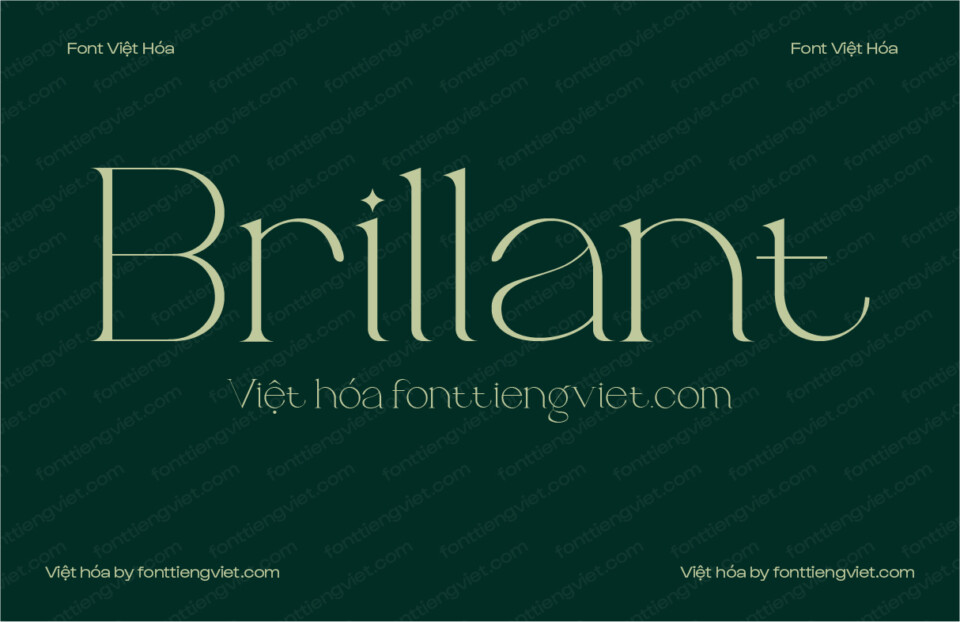
Font Việt hóa 1FTV VIP Brillant
Giới thiệu về bộ Font Việt hóa 1FTV VIP Brillant
Trong thế giới thiết kế đồ họa hiện đại, việc lựa chọn một phông chữ phù hợp đóng vai trò quyết định đến linh hồn của tác phẩm. Font Việt hóa 1FTV VIP Brillant nổi lên như một hiện tượng trong cộng đồng designer Việt Nam nhờ sự kết hợp hoàn hảo giữa nét cổ điển và hơi thở đương đại. Đây là bộ Font Miễn Phí được tinh chỉnh kỹ lưỡng để hỗ trợ đầy đủ các ký tự tiếng Việt, giúp người dùng không còn lo lắng về lỗi hiển thị dấu hay khoảng cách chữ không đều. Với cấu trúc đường nét thanh mảnh nhưng vô cùng chắc chắn, bộ chữ này mang lại cảm giác chuyên nghiệp và đẳng cấp cho mọi khung hình. Đặc biệt, phiên bản 1FTV VIP Brillant này đã được tối ưu hóa để hiển thị sắc nét trên cả màn hình kỹ thuật số lẫn các ấn phẩm in ấn vật lý, đáp ứng nhu cầu khắt khe của các chuyên gia sáng tạo.
Đặc điểm nổi bật của Font Việt hóa 1FTV VIP Brillant
Thiết kế sang trọng và tinh tế
Điều đầu tiên khiến Font Việt hóa 1FTV VIP Brillant thu hút sự chú ý chính là sự chỉn chu trong từng nét chữ. Các đường cong được vuốt nhẹ nhàng, tạo nên sự uyển chuyển nhưng không kém phần mạnh mẽ. Đây là lựa chọn lý tưởng cho các dự án thiết kế thương hiệu cao cấp, thiệp mời sự kiện hoặc các bìa tạp chí thời trang. Sự cân bằng giữa các ký tự giúp văn bản trở nên dễ đọc, tạo cảm giác dễ chịu cho người xem ngay từ cái nhìn đầu tiên.
Khả năng tương thích đa dạng
Ứng dụng thực tế của Font Việt hóa 1FTV VIP Brillant
Trong thiết kế truyền thông và quảng cáo
Với phong cách VIP đầy ấn tượng, phông chữ này thường xuyên xuất hiện trong các chiến dịch quảng cáo sản phẩm làm đẹp, trang sức và bất động sản. Việc sử dụng Font Việt hóa 1FTV VIP Brillant giúp tiêu đề của bạn trở nên nổi bật, thu hút sự chú ý của khách hàng mục tiêu và nâng tầm giá trị cho thông điệp truyền tải. Những đường nét tinh xảo của bộ chữ góp phần xây dựng lòng tin và sự chuyên nghiệp cho hình ảnh thương hiệu trong mắt công chúng.
Trong giáo dục và đời sống hàng ngày
Tại các nhà trường, các thầy cô giáo có thể ứng dụng bộ chữ này để thiết kế bằng khen, chứng chỉ hoặc các tài liệu giảng dạy sinh động. Sự rõ ràng của Font Việt hóa 1FTV VIP Brillant giúp học sinh dễ dàng tiếp nhận thông tin, đồng thời kích thích óc thẩm mỹ của các em thông qua những trình bày đẹp mắt. Ngoài ra, bạn cũng có thể dùng nó để trang trí ảnh cá nhân, viết blog hoặc tạo ra những lời chúc ý nghĩa gửi tặng người thân và bạn bè vào các dịp lễ đặc biệt.
Kết luận về bộ Font Việt hóa 1FTV VIP Brillant
Tổng kết lại, đây là một tài nguyên vô giá dành cho bất kỳ ai đang tìm kiếm sự đột phá trong phong cách thiết kế của mình. Sự tỉ mỉ trong quá trình Việt hóa đã giúp bộ chữ này trở nên gần gũi và dễ sử dụng hơn bao giờ hết với người dùng trong nước. Nếu bạn đang muốn làm mới các tác phẩm nghệ thuật hay đơn giản là tìm kiếm một làn gió mới cho các tài liệu học tập, đừng ngần ngại trải nghiệm ngay Font Miễn Phí, Font Việt Hóa, Font Việt hóa 1FTV VIP Brillant. Chúc các bạn sẽ có những trải nghiệm sáng tạo tuyệt vời và tạo ra những sản phẩm ấn tượng với bộ font chữ đẳng cấp này.